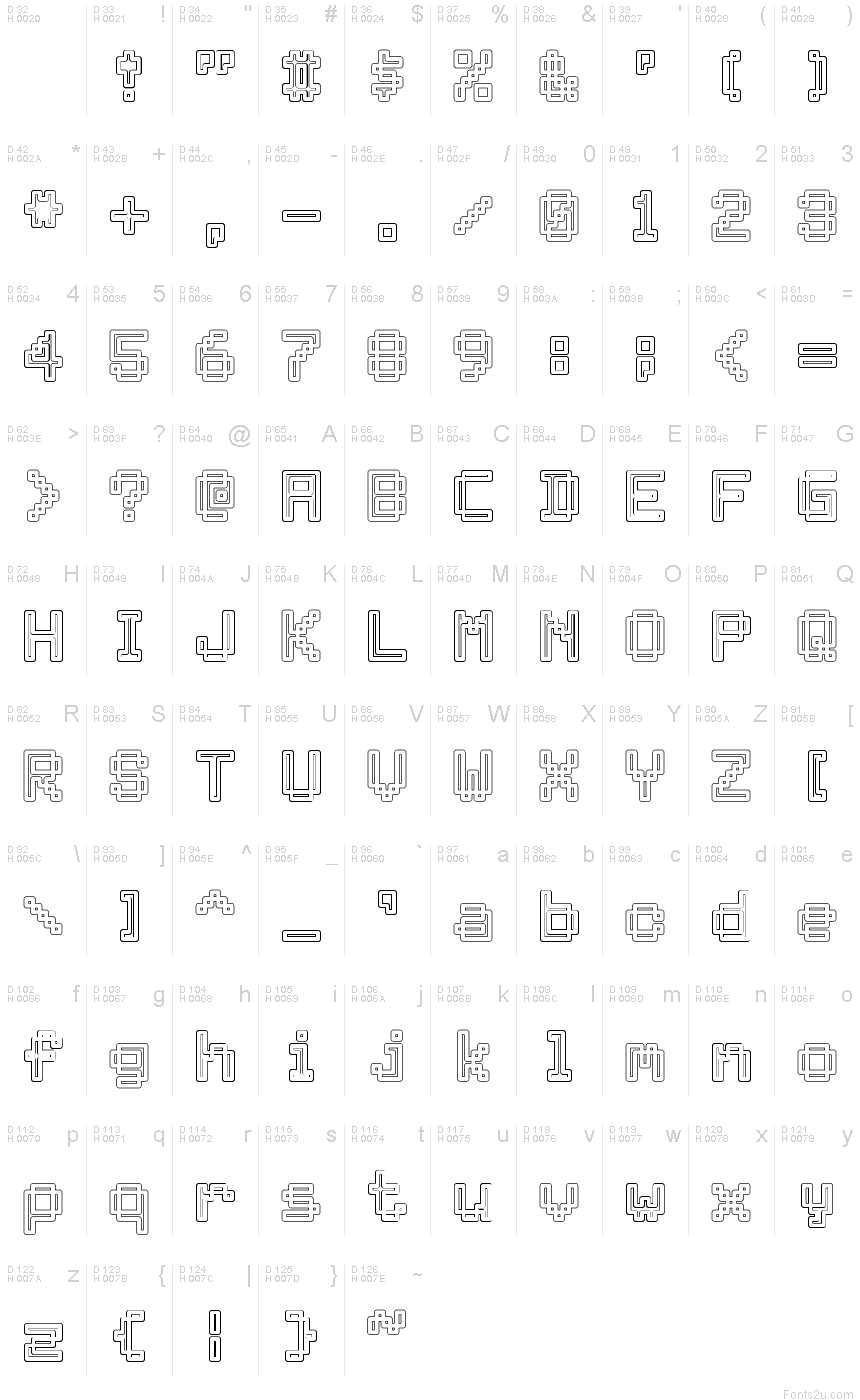
Archway هو خط مجاني من نوع techno display يبدو كأنابيب مضيئة منحنية على شكل أحرف. يتكون كل حرف من خطوط محيطية متداخلة، مما يخلق بنية مفرغة تشبه المتاهة تدمج بين طابع الألعاب الكلاسيكية (Retro Arcade) وواجهات المستخدم المستقبلية. تمنحه الزوايا الدائرية وسمك الخط المتساوي ملمساً ناعماً يشبه البلاستيك، بينما تضيف الخطوط المتعددة الطبقات عمقاً وحركة فورية دون الحاجة إلى مؤثرات إضافية.
باستخدام Archway، يمكنك إضافة طاقة خيال علمي جريئة مباشرة إلى شعارات الألعاب، أغلفة الموسيقى الإلكترونية، ملصقات المهرجانات، هويات العلامات التجارية التقنية، تراكبات البث المباشر، وعناوين الفن الرقمي. يتألق هذا الخط المجاني عند استخدامه بأحجام كبيرة، حيث تظل تفاصيله المتداخلة واضحة ومقروءة. نسّق Archway مع خط هندسي بلا زوائد (Sans Serif) للنص الأساسي واترك لهذا الخط الـ techno أن يتصدر العناوين الكبيرة والمتوهجة.